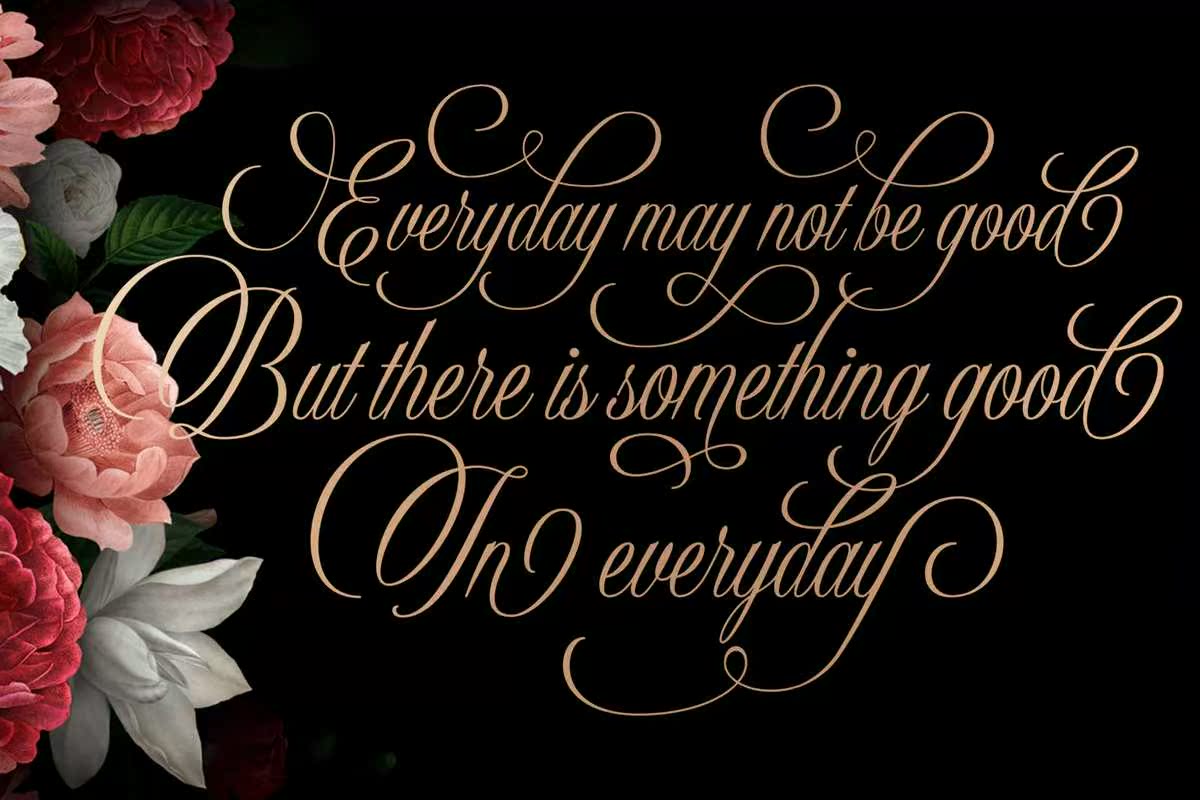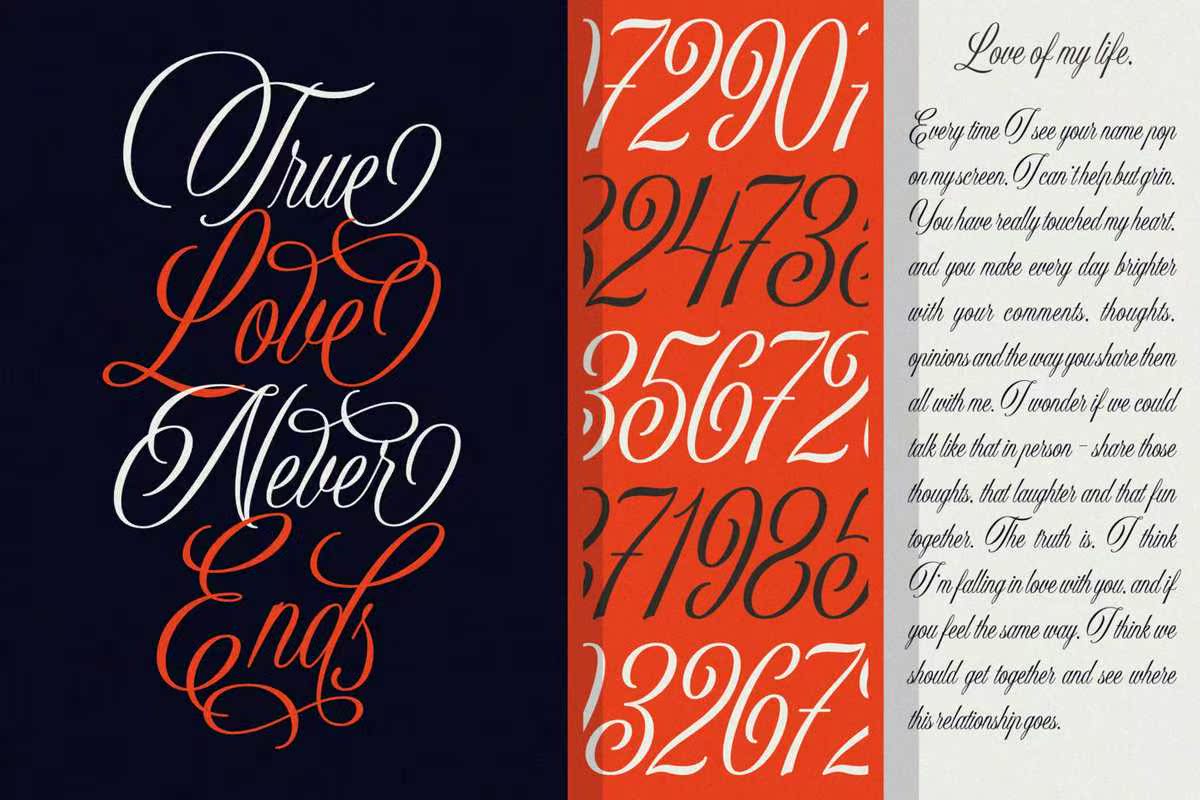
Sholariaded设计的Tobeaclean和奢华的DisplayScriptFont。灵感来自VintageCopper Plate样式。小心地定义“flow”结果。镜头之间没有任何连接。Tonof“Essential”将与StopLaying互换,大约400字形。此字体将适用于您的任何项目。品牌、报价、标题、,浪漫的字母和许多字母。鞋底设计为圆顶和奢华的显示脚本字体。灵感来自Vintage铜板样式。小心地消除“流动”结果。镜头之间没有任何连接。Tonof“Essential”可替换为StopLaying,大约400字形。此字体将适用于您的任何项目。品牌、报价、标题、,浪漫情书和曼尼摩尔。